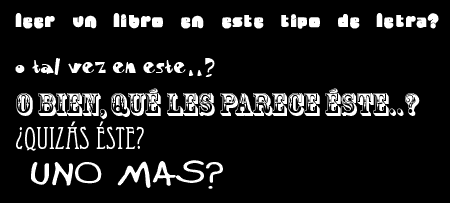
Es común ver por la web varios sitios que ofrecen tipografí­as gratis. Por desgracia, mucho del material para descargar es basura ornamental imposible de utilizar como texto en un diseño serio y legible.
La prueba ácida de cualquier tipografí­a es “¿cómo funciona en un bloque de texto?”. ¿Alguno se imagina
Las tipografí­as que de estudiantes creemos cool o aquellas que actualmente podemos bajar gratis de muchos sitios, suelen ser “garbage” tipográfica.
No obstante, aquí­ hay un buen sitio donde se pueden descargar gratis 30 tipos de buena calidad para crear diseños funcionales.
Tal vez esta pequeña reflexión sirva para generar un poco de respeto a las “aburridas” Arial, Helvetica, Univers, Times, Gill Sans, Garamond y otros diseños por los que la gente común no siente mayor aprecio y que sin embargo son los pilares de la legibilidad actual.